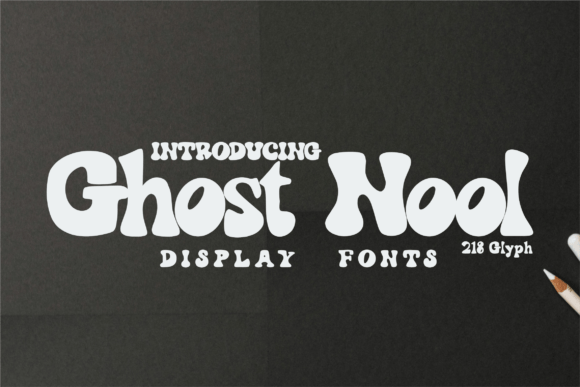
Ghost Nool
Ghost Noolのような高品質の素材をお探しの場合、このプレミアムパッケージはクリエイティブなプロジェクトに素晴らしい選択です。
POD(オンデマンド印刷)製品、結婚式の招待状、またはソーシャルメディアのグラフィックを作成している場合でも、Ghost Noolは理想的です。